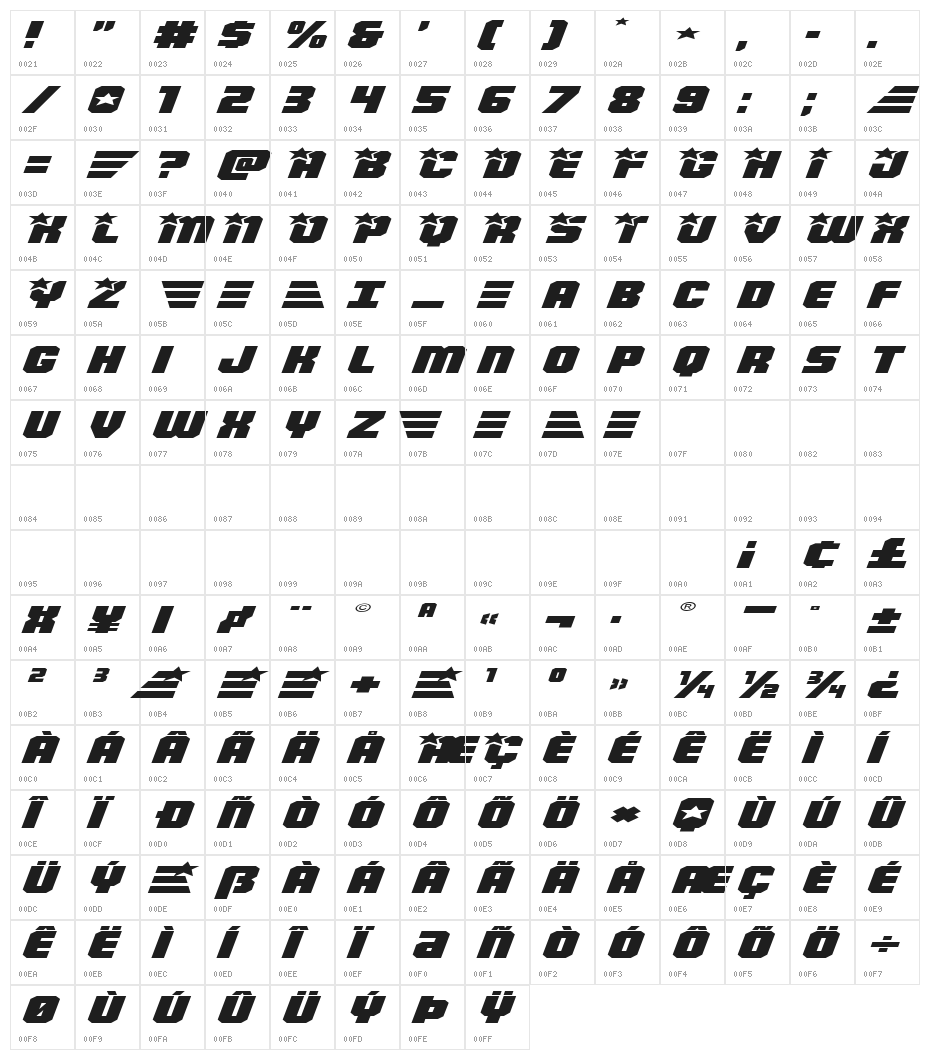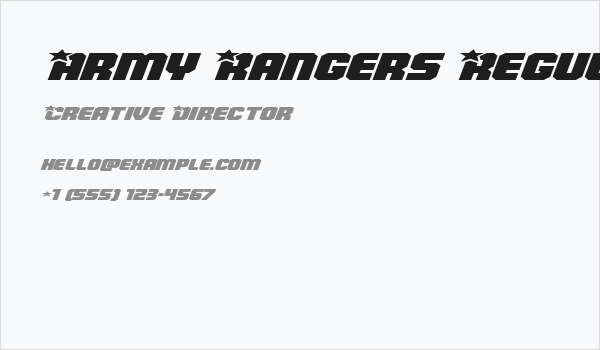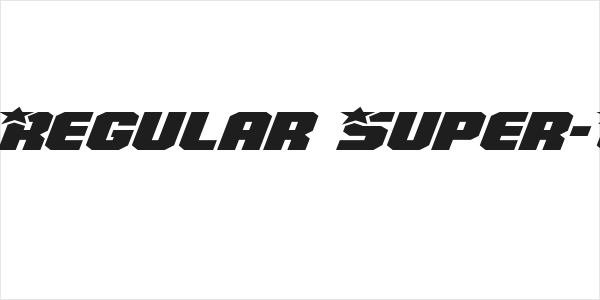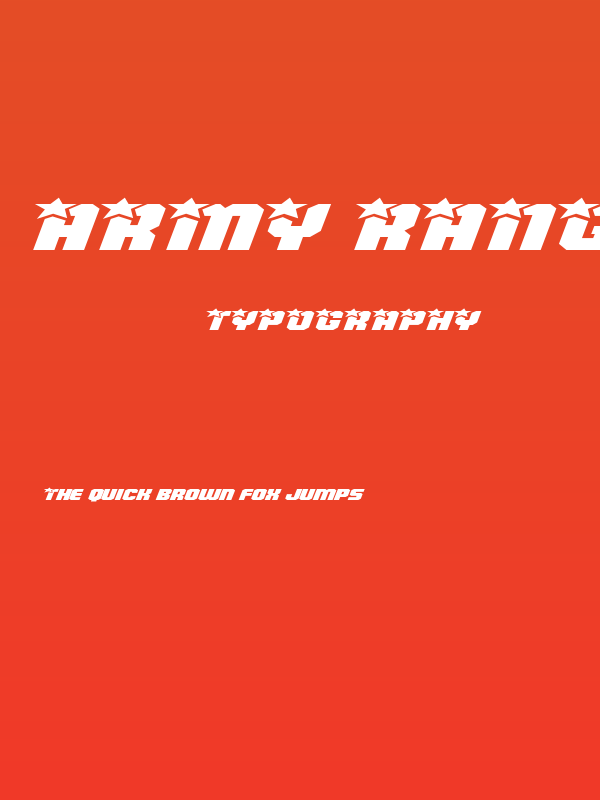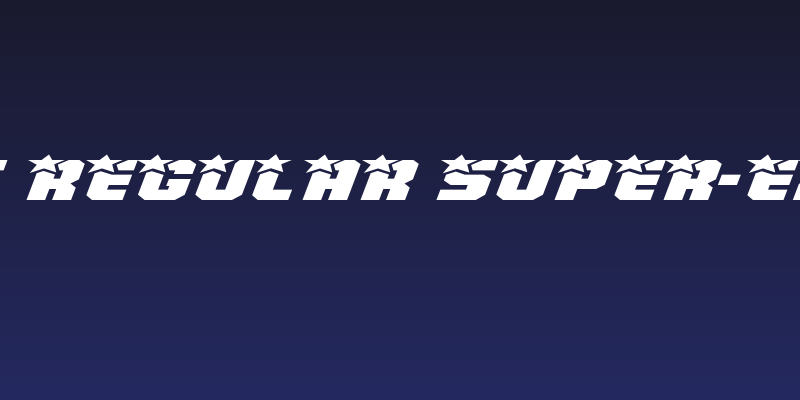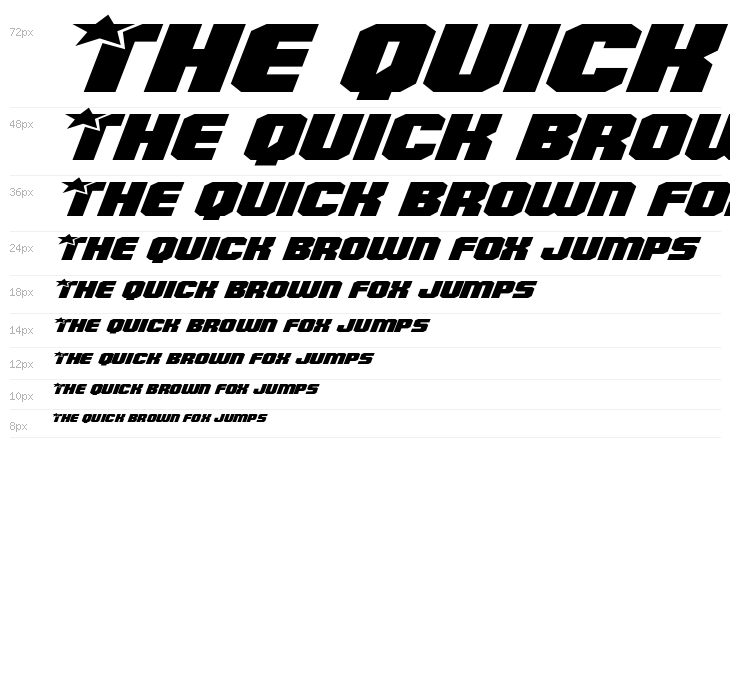
Army Rangers Regular Super-Expanded Italic Font
| Vorgeschlagene Projekte | Ideal for military-themed posters, video game titles, sports team branding, or any project needing a bold, authoritative look. |